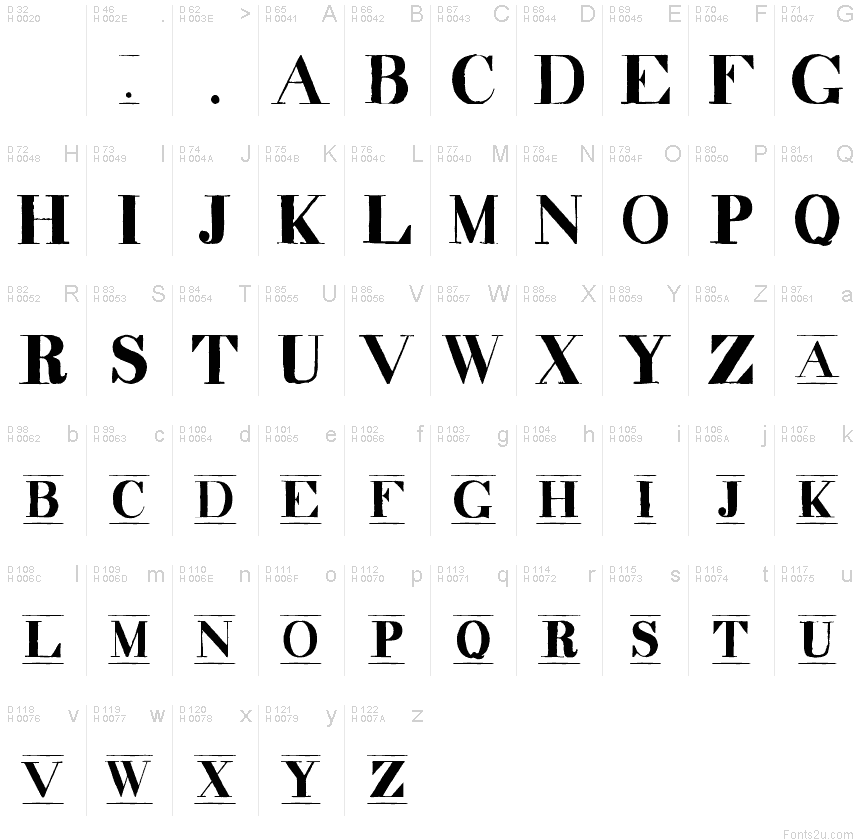
Decadence Itd Condensed Marquee autorstwa Stevena J. Lundeena to darmowy, stylizowany na zniszczony krój typu display. Wysoka, wąska konstrukcja i ślady zużycia sprawiają, że wygląda jak farba drukarska starta ze starej matrycy. Wyraziste szeryfy i ciasny rytm nadają mu charakteru, który łączy klimat dawnych afiszy kinowych z prasą drukarską – jest śmiały, wyrazisty i lekko drapieżny.
Decadence Itd Condensed Marquee świetnie sprawdza się na plakatach koncertowych, w tytułach filmowych, na opakowaniach vintage, etykietach whisky czy produktów aptecznych, okładkach książek, nagłówkach redakcyjnych i gadżetach zespołów muzycznych, gdzie potrzebny jest efekt surowości. Ten darmowy font najlepiej wygląda, gdy ma przestrzeń – używaj go w dużych rozmiarach – i w połączeniu z czystym krojem bezszeryfowym, takim jak Inter czy Helvetica, w tekstach pomocniczych.